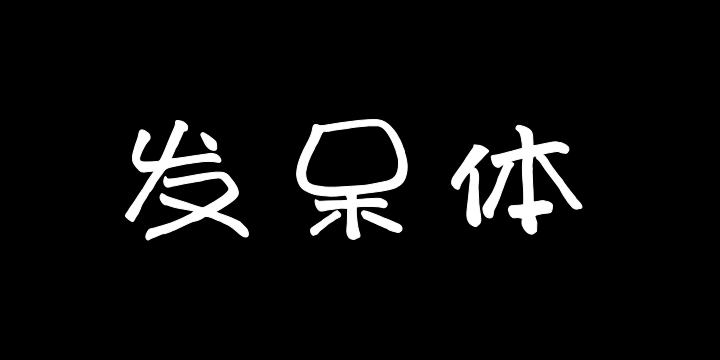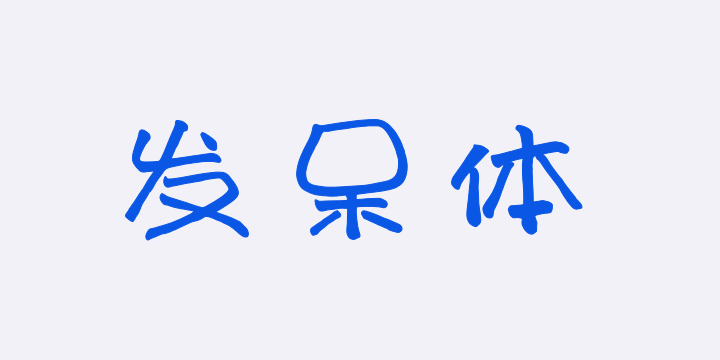
上首发呆体 By 上首造字 商用字体
字体全名: 上首发呆体
铸字厂: 上首造字
设计师: 胡博剑
字体简介: 上首发呆体,字体笔画摒弃规整与刻板,呈现出随性、自然的弯曲与变形。部分笔画像是不经意间的勾勒,如同人在发呆时思绪的随意飘荡。字形结构也不追求绝对对称与平衡,带有一种自由散漫的布局,恰似发呆时思维的无拘无束。整体视觉效果轻松、诙谐,与传统严肃规整的字体形成鲜明对比。这种独特的风格能够在众多字体中迅速吸引目光。适用于搭配标志、广告标语、商业广告等高端属性。